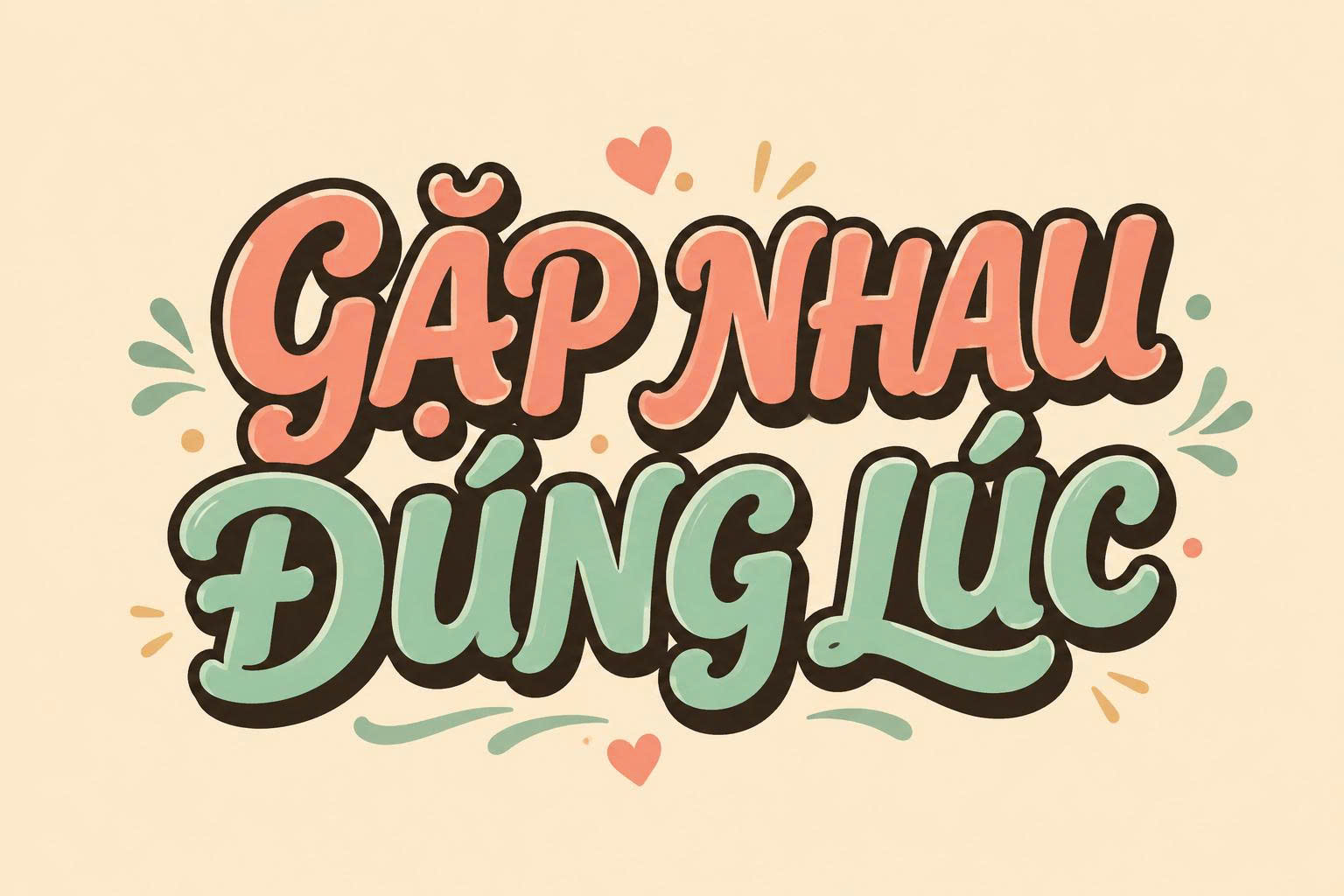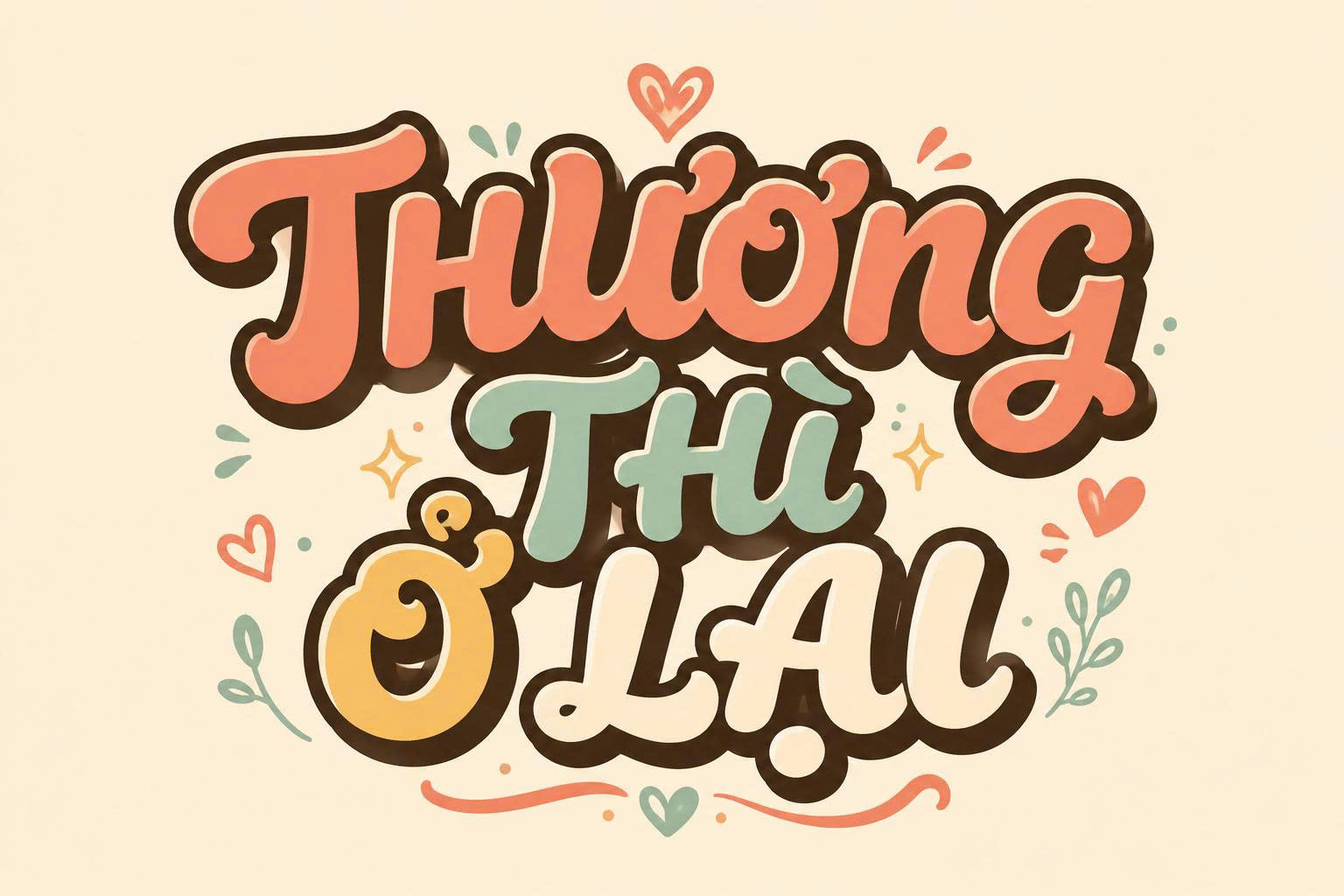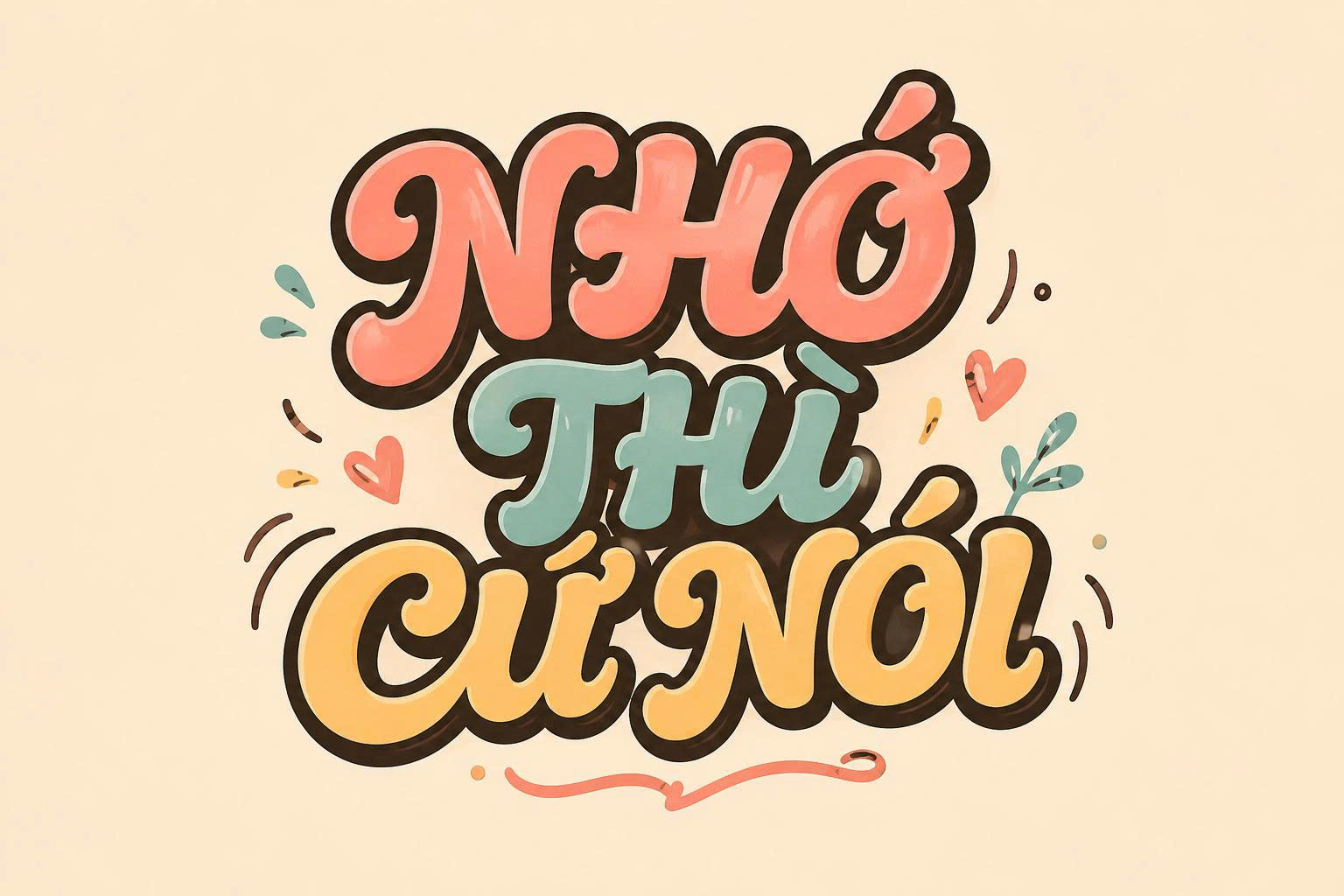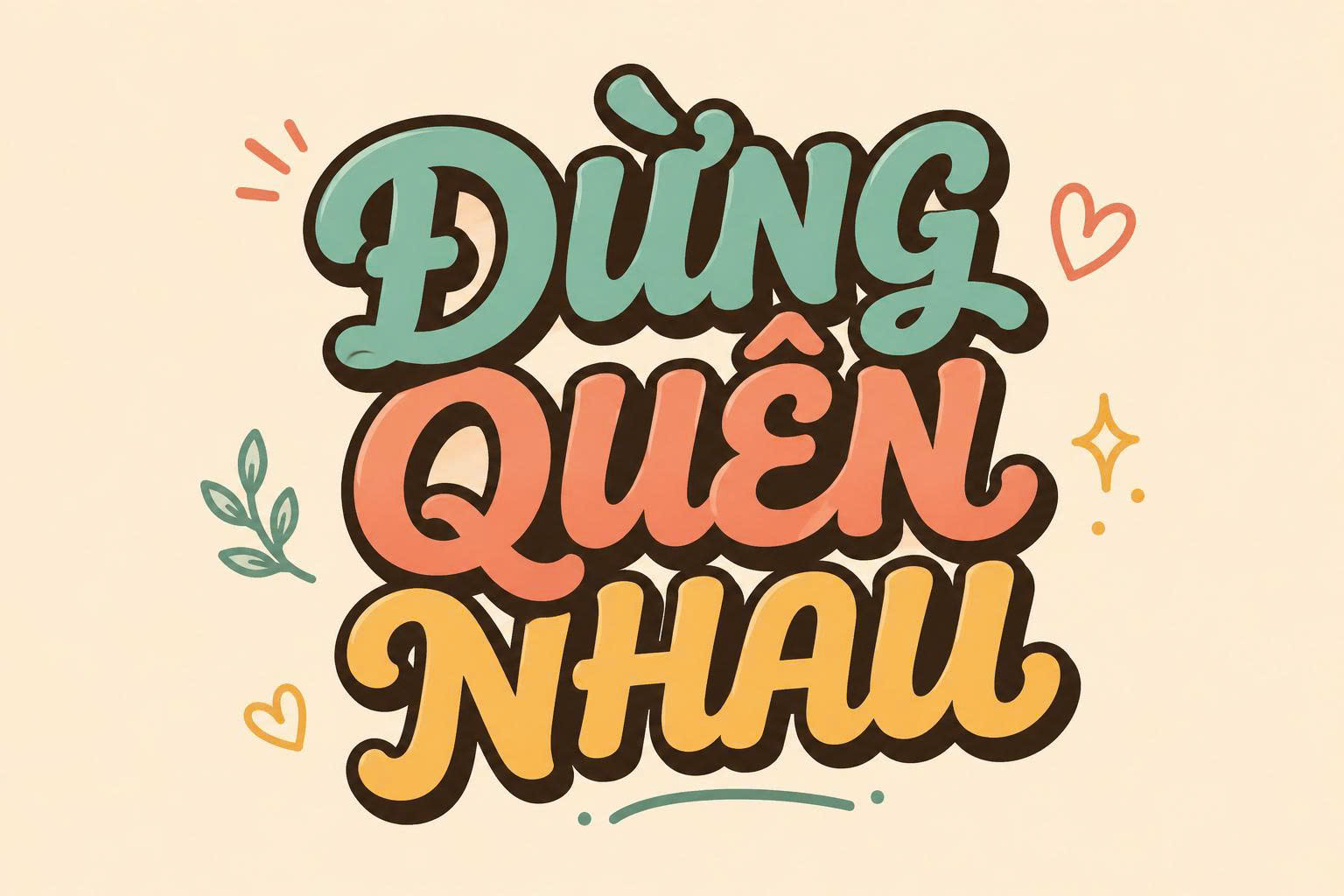
Font chữ SVN-Bali Script Việt hóa là bộ phông chữ thuộc dòng Brush Script mang phong cách viết tay đầy phóng khoáng, tự nhiên và tràn đầy năng lượng. Với những đường nét mô phỏng nét cọ vẽ có độ xước nhẹ và nhịp điệu bay bổng, SVN-Bali Script là lựa chọn hoàn hảo cho các thiết kế logo, bao bì sản phẩm hoặc các ấn phẩm quảng cáo cần sự phá cách và mang hơi thở của mùa hè nhiệt đới. Doozypack.vn cung cấp link tải font SVN-Bali Script chuẩn, giúp bạn sở hữu bộ phông chữ nghệ thuật không lỗi dấu thanh để hiện thực hóa các ý tưởng thiết kế độc đáo.
Đặc điểm thẩm mỹ của font SVN-Bali Script Việt hóa
SVN-Bali Script không chỉ đơn thuần là một phông chữ viết tay; nó mang trong mình tinh thần của sự tự do và tính nghệ thuật thủ công (handmade) đặc trưng.
Phong cách Brush Script phóng khoáng và tự nhiên
Đặc trưng lớn nhất của font chữ SVN-Bali Script Việt hóa là cấu trúc nét chữ có độ dày không đồng đều, mô phỏng lại áp lực của bút lông trên bề mặt giấy thô nhám. Các chi tiết xước (texture) li ti trong từng nét chữ tạo nên chiều sâu thị giác, giúp văn bản trông sống động và có hồn hơn. Phong cách này cực kỳ phù hợp cho những thương hiệu muốn nhấn mạnh tính bản bản địa, sự gần gũi với thiên nhiên hoặc tinh thần năng động.
Hệ thống ký tự Việt hóa chỉn chu, chuyên nghiệp
Nằm trong hệ sinh thái font SVN nổi tiếng, Bali Script đã được tinh chỉnh lại toàn bộ hệ thống dấu thanh tiếng Việt. Các dấu sắc, huyền, hỏi, ngã, nặng được thiết kế mộc mạc, hài hòa với cấu trúc brush của thân chữ, đảm bảo không làm mất đi độ bay bổng đặc trưng của bộ font. Việc sử dụng bản font SVN-Bali Script Việt hóa chuẩn giúp bạn gõ các slogan như “Sáng tạo không giới hạn” hay “Tận hưởng mùa hè” một cách trọn vẹn và thẩm mỹ.
Tại sao designer nên download font SVN-Bali Script cho thiết kế bao bì?
Trong ngành sản xuất bao bì tại Doozypack.vn, Bali Script thường xuyên được ưu tiên cho các dự án cần tạo điểm nhấn cá tính:
- Tạo dấu ấn thương hiệu độc bản: Phong cách viết tay giúp bao bì sản phẩm của bạn thoát khỏi sự khô cứng, tạo cảm giác thân thiện và cao cấp hơn trong mắt người tiêu dùng.
- Phát huy tối đa hiệu ứng hình ảnh: Cấu trúc chữ của Bali Script rất phù hợp để kết hợp với các hình vẽ minh họa (illustration) hoặc ảnh chụp sản phẩm phong cách lifestyle.
- Tính ứng dụng đa dạng: Bạn có thể dùng font này cho cả nhãn dán chai lọ, vỏ hộp quà tặng hay các banner quảng cáo trên mạng xã hội.
04 Ứng dụng thực tế của Bali Script trong sản xuất bao bì tại Doozypack.vn
Sự năng động của Bali Script mang lại hiệu quả thị giác đặc biệt trên các ấn phẩm thực tế do Doozypack.vn sản xuất:
- Hộp mỹ phẩm & Tinh dầu: Nét chữ Brush bay bổng rất hợp với các sản phẩm làm đẹp thiên nhiên, tạo cảm giác thư giãn và sang trọng.
- Bao bì thực phẩm (Trà, Cà phê, Bánh ngọt): Dùng làm tiêu đề chính giúp sản phẩm trông ngon miệng và mang đậm tính thủ công.
- Tem nhãn đồ uống giải khát: Kết hợp Bali Script với các tông màu rực rỡ để tạo nên bộ nhãn chai nước ép hoặc trà trái cây tươi mát cho mùa hè.
- Túi giấy thời trang: Tên shop in bằng font Bali Script trên túi giấy trắng cán màng mờ tạo phong cách trẻ trung và cá tính.
03 Lưu ý kỹ thuật khi in ấn font chữ viết tay (brush) nét xước
Sản xuất bao bì sử dụng phông chữ có nhiều chi tiết texture như Bali Script đòi hỏi designer cần lưu ý một số vấn đề kỹ thuật tại xưởng in chuyên nghiệp:
- Xử lý nét xước khi ép kim (Hot Stamping): Các nét xước li ti của Bali Script có thể bị bết mực hoặc không bám nhũ nếu khuôn ép không được xử lý kỹ. Doozypack.vn khuyên bạn nên “clean” bớt các chi tiết xước quá vụn trước khi làm khuôn để đảm bảo độ sắc nét.
- Hạn chế in size quá nhỏ trên giấy thô: Giấy Kraft có độ thấm mực cao, các nét cọ mảnh của Bali Script dễ bị nhòe nếu in kích thước dưới 10pt. Hãy giữ size chữ đủ lớn để bảo đảm tính dễ đọc.